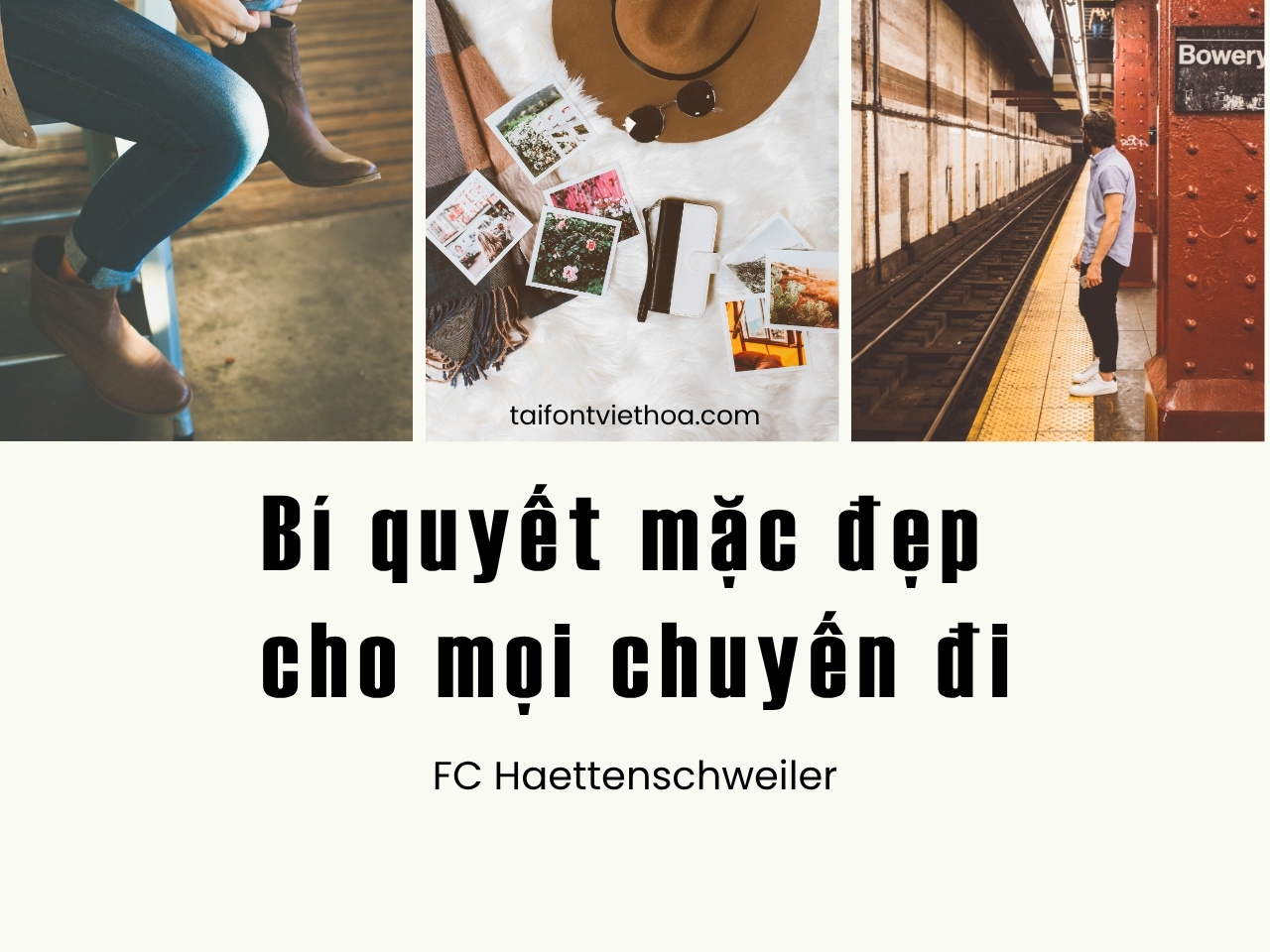
Font việt hóa FC Haettenschweiler
Tác giả Font: Monotype Typography
Giới thiệu về font Haettenschweiler và phiên bản Việt hóa
FC Haettenschweiler là phiên bản Việt hóa mới từ font gốc “Haettenschweiler” – một kiểu chữ sans-serif condensed mang tính biểu tượng, được sáng tạo bởi nhà thiết kế người Thụy Sĩ Walter Haettenschweiler từ năm 1954. Font này từng nổi tiếng khi được Microsoft tích hợp mặc định trong bộ font của Windows 95, gắn liền với những thiết kế tiêu đề đậm, phong cách báo chí cổ điển và truyền thông đại chúng trong suốt thập niên 90 đến đầu 2000. Với cấu trúc gọn gàng, nén chặt và đường nét mạnh mẽ, Haettenschweiler được đánh giá cao trong các thiết kế cần tạo điểm nhấn mạnh về thị giác.
Khác biệt rõ so với bản Việt hóa “Font VN Haettenschweiler” từng được biết đến trước đó, phiên bản FC Haettenschweiler do cộng đồng Font Chuẩn thực hiện đã được tinh chỉnh lại hoàn toàn theo chuẩn Unicode, tối ưu cho bảng chữ tiếng Việt có dấu. Các chi tiết kỹ thuật như kerning, dấu thanh và chiều cao chữ được xử lý thủ công để duy trì sự sắc nét và đồng bộ với bản gốc.
Font này đã được taifontviethoa.com tuyển chọn, kiểm duyệt và chia sẻ như một lựa chọn đáng tin cậy cho nhà thiết kế Việt đang tìm kiếm một kiểu chữ cổ điển, đậm chất báo chí nhưng vẫn linh hoạt trong ứng dụng hiện đại như poster, tiêu đề, thiết kế truyền thông và nhận diện thương hiệu mạnh mẽ.
Đặc điểm thiết kế và ứng dụng thực tiễn
FC Haettenschweiler nổi bật với kiểu dáng condensed (thu hẹp chiều ngang) nhưng vẫn giữ được độ dày cao và nét chắc chắn, mạnh mẽ trong từng ký tự. Các chữ cái không có chân, đường nét thẳng, bo góc nhẹ, tạo nên cảm giác gọn gàng, dồn lực – rất phù hợp với phong cách thiết kế cổ điển nhưng vẫn hiện đại. Font không có nhiều biến thể stylistic nhưng chính sự đơn giản này giúp nó truyền tải thông điệp trực diện và hiệu quả hơn.
Font đặc biệt phù hợp với tiêu đề báo chí, poster cổ điển, thiết kế bao bì retro, banner quảng cáo hoặc các sản phẩm đòi hỏi sự chú ý cao. Các ngành nghề như truyền thông, xuất bản, thể thao, thời trang retro, công nghệ hoài cổ hoặc lĩnh vực sáng tạo mang tính thương hiệu đều có thể khai thác hiệu quả FC Haettenschweiler.